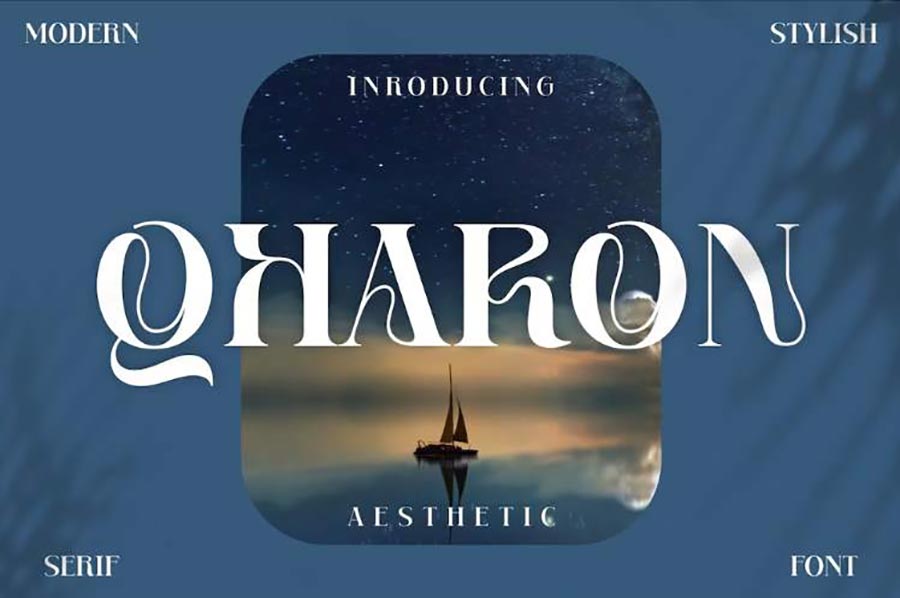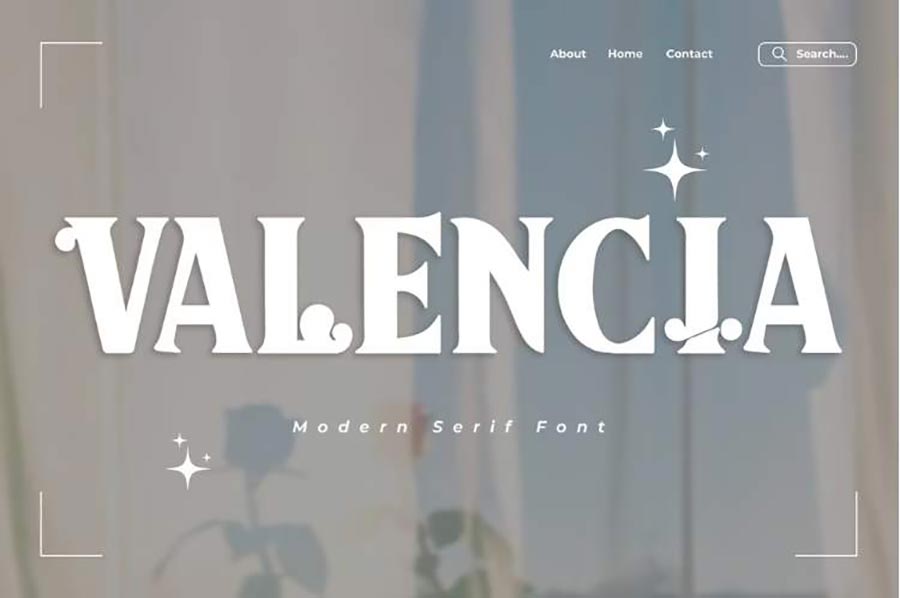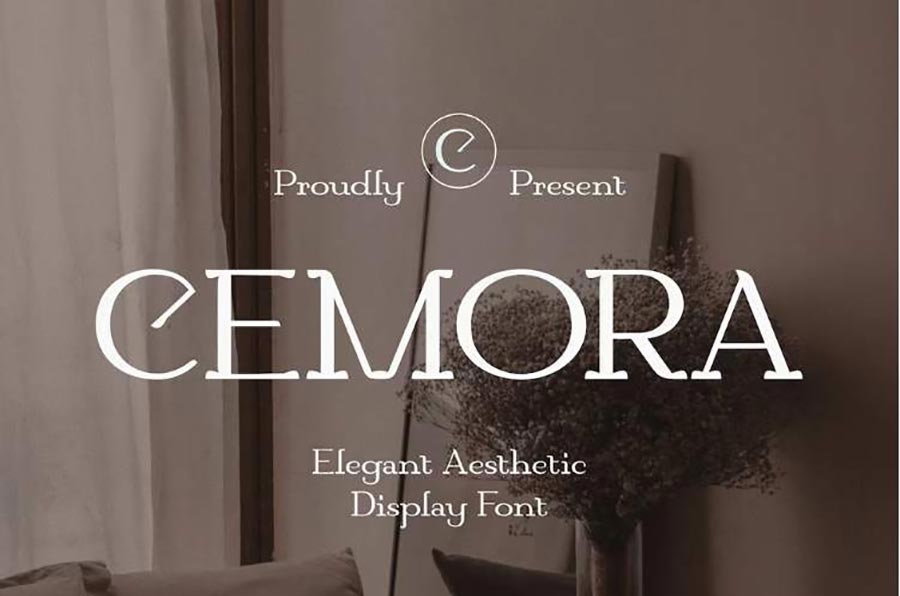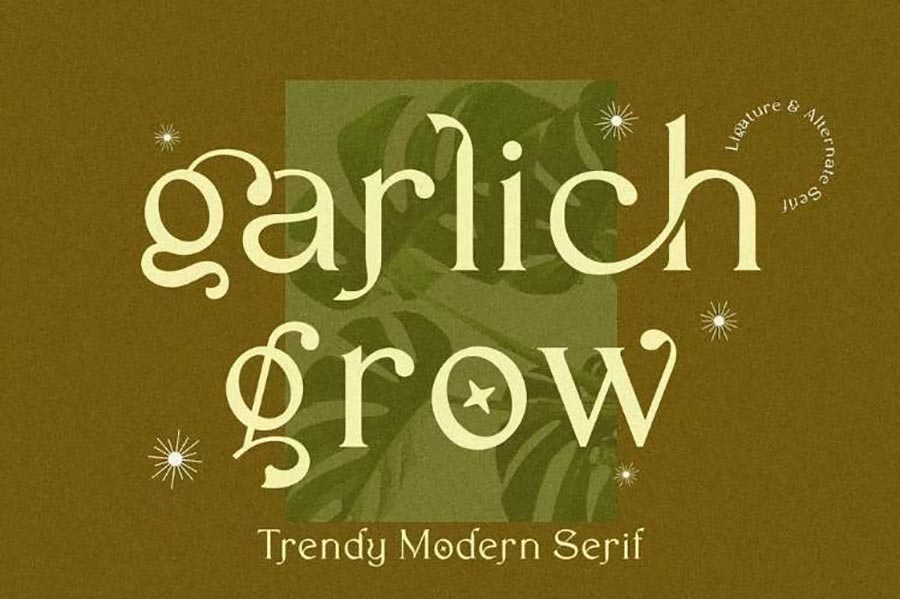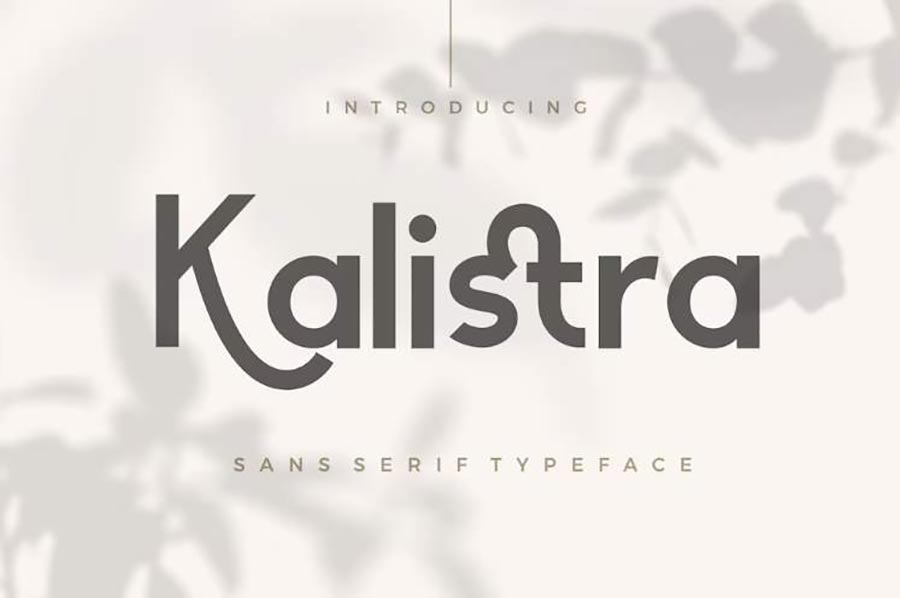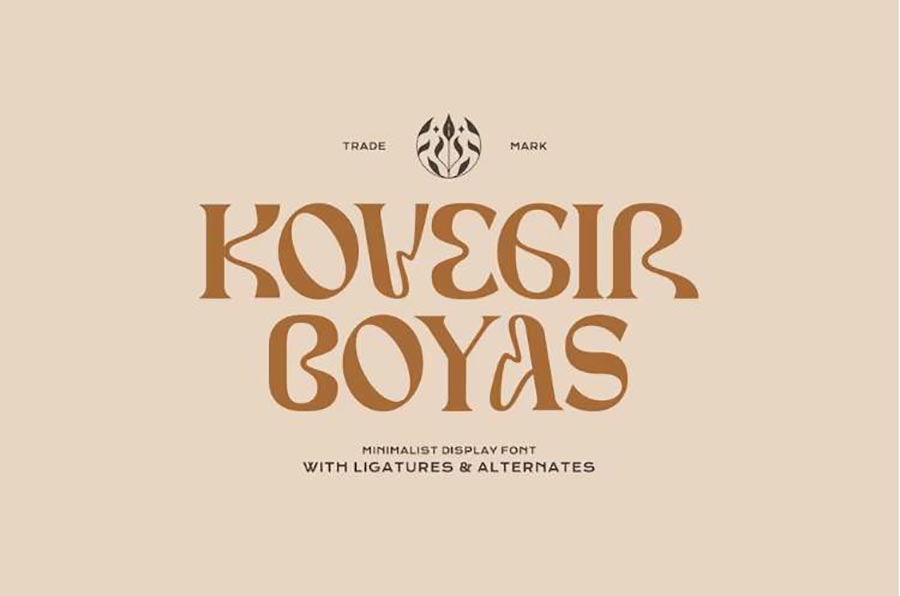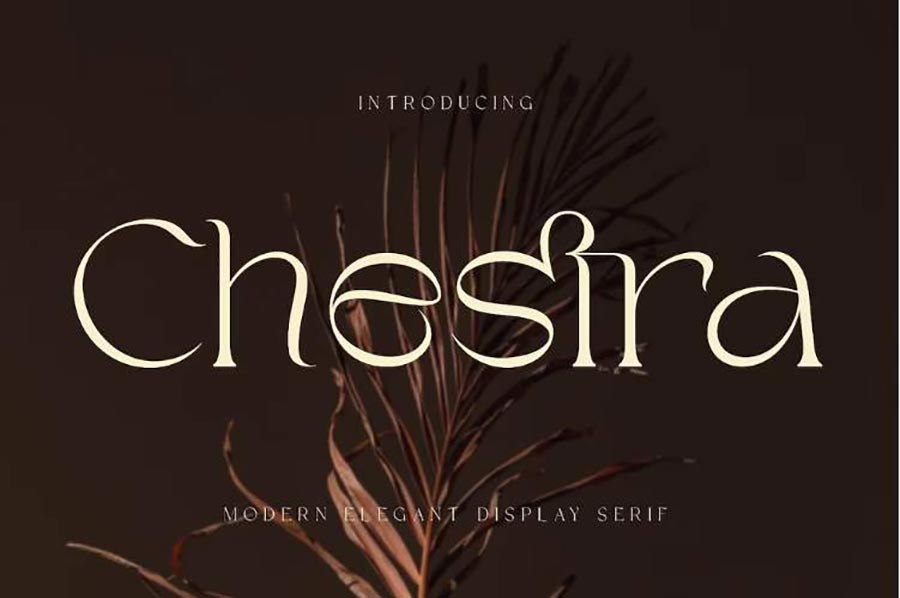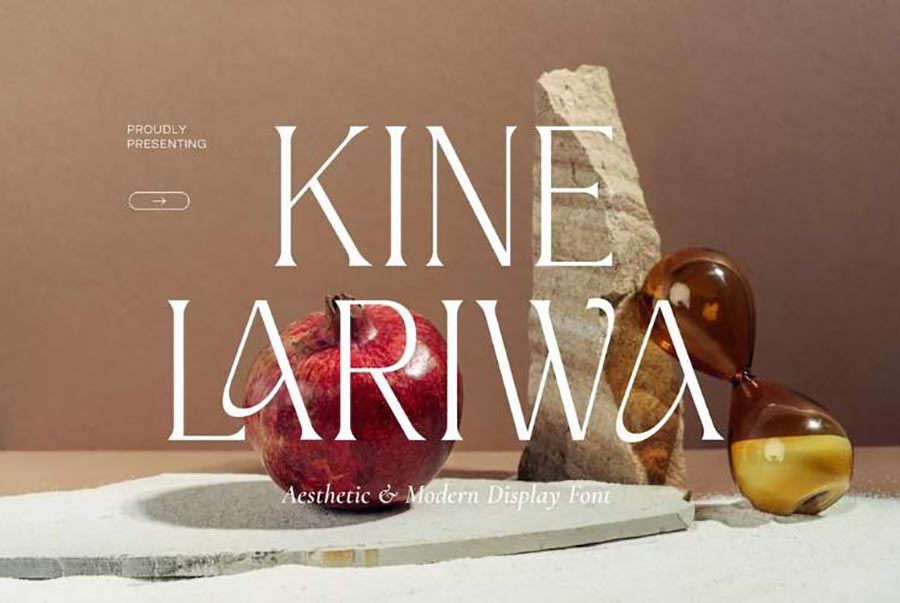
Fonts Aesthetic Là Gì?
Fonts Aesthetic là thuật ngữ dùng để chỉ những kiểu chữ mang tính thẩm mỹ cao, thường được thiết kế với phong cách hiện đại, tinh tế và phù hợp với nhiều loại hình sáng tạo. Những fonts này thường được sử dụng trong các dự án như:
- Thiết kế logo
- Poster quảng cáo
- Thiệp mời
- Nội dung mạng xã hội
- Website và blog cá nhân.
Với khả năng truyền tải cảm xúc và thông điệp một cách tinh tế, **fonts Aesthetic** đã trở thành lựa chọn hàng đầu của các designer chuyên nghiệp.